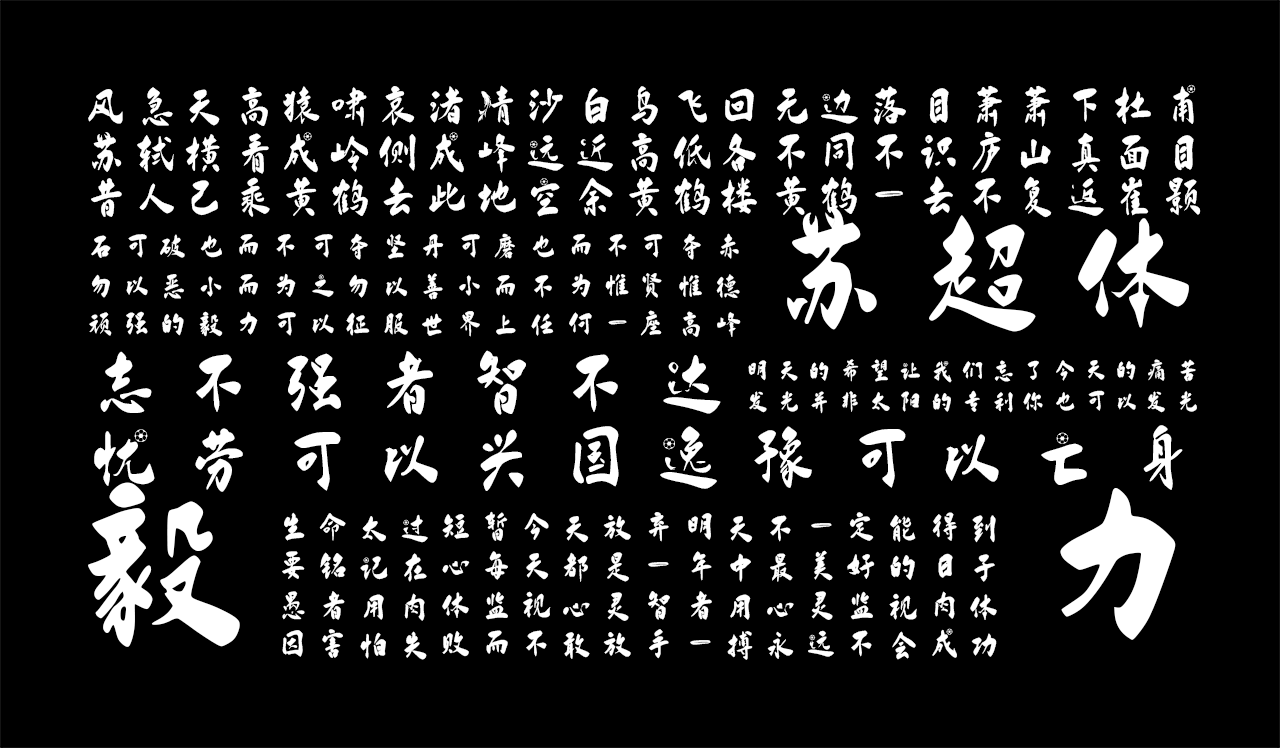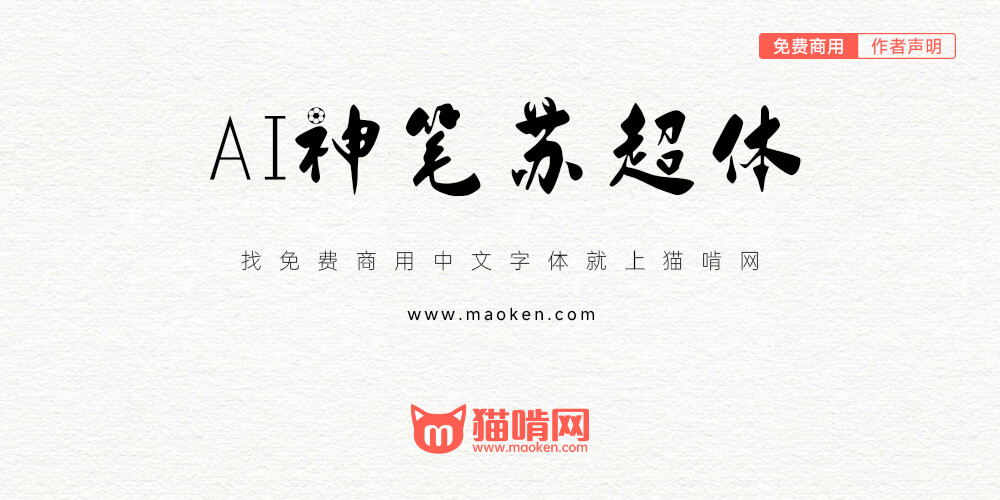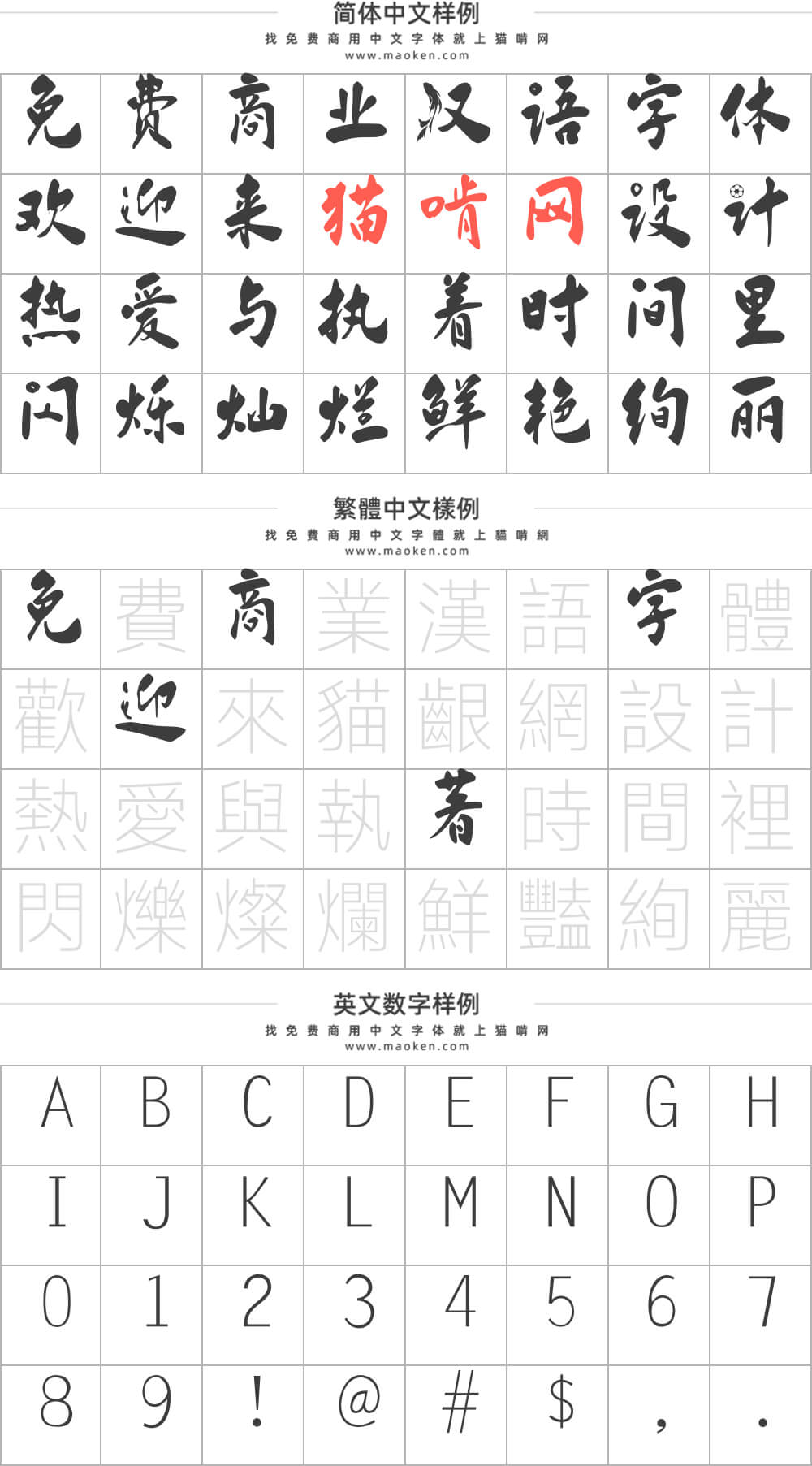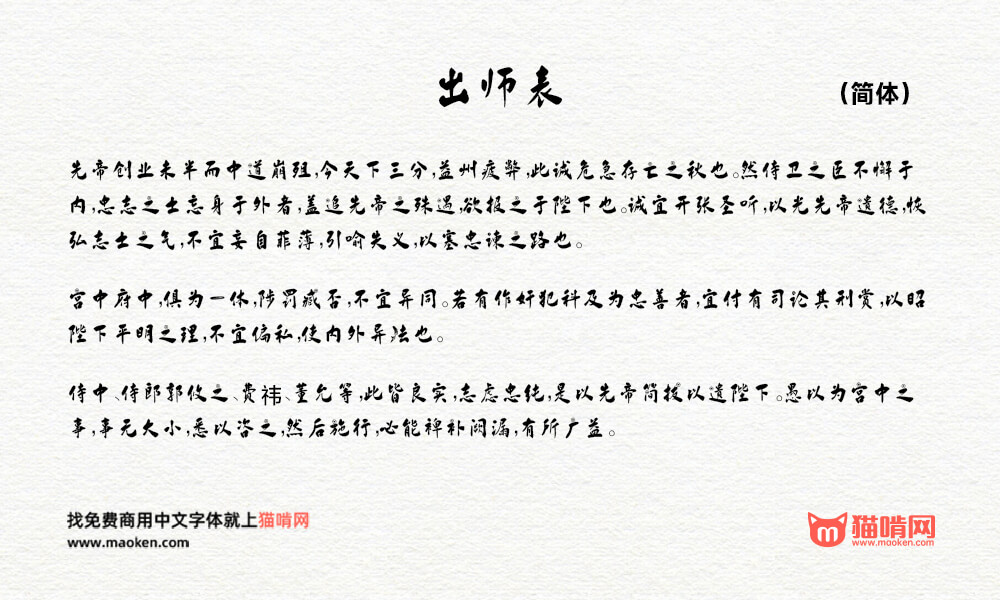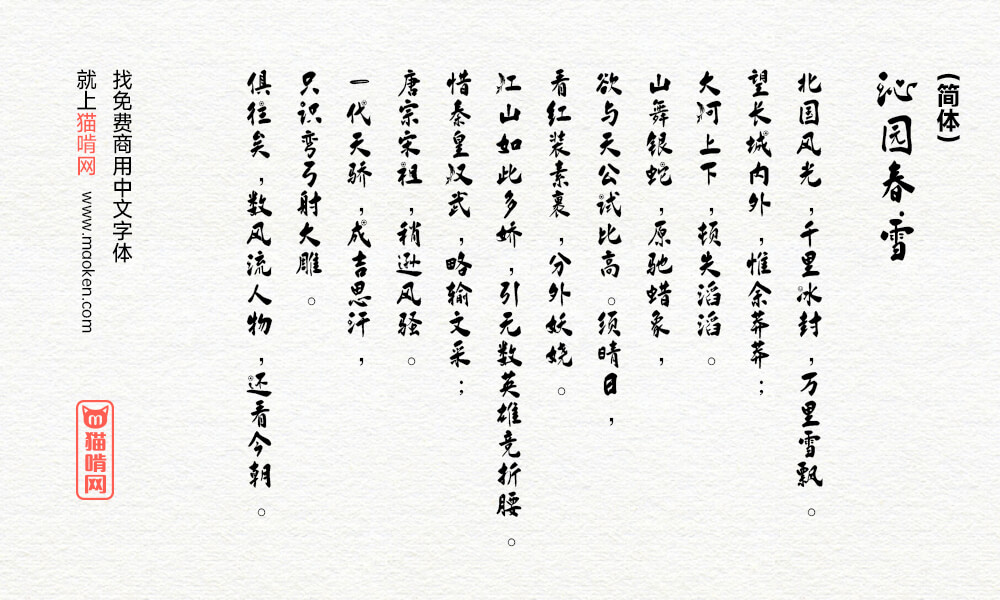
AI神笔苏超体是一款由字体家AI神笔造字生成的艺术字体,笔画似毛笔轻提重按,起笔藏锋如指尖轻触纸面的柔缓,收笔露锋若丝线渐细飘远。横画舒展如平展布帛,中段饱满有弹性,竖画挺拔似立木,直中带微弧显韧劲。转折处圆转无棱角,如卵石相触的温润。偶见飞白如发丝轻扬,笔画边缘有自然晕染感。骨架方正却藏灵动,刚柔相济,似能触到笔尖在纸上的轻重提按,气韵连贯如流水行舟。将笔画稍作修改,增添时尚活泼的感觉,古今结合。适合用于一些广告标题、平面文案、海报标题、网页广告用字的编辑。
且不提完全不搭、粗细不匀的祖传英文,不全角的全角标点,字体家是完全不打算解决AI字形上飘的问题吗🤔